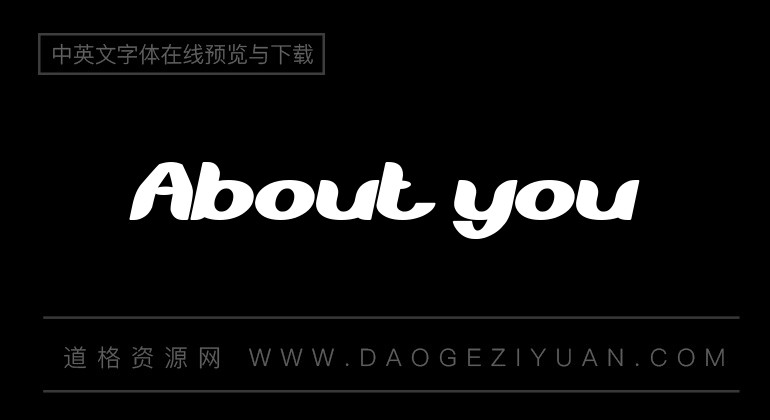
About you
About You 是一个比较流行的英文字体,它的特点是简洁明了,笔画舒缓,字形细腻,显示效果非常优美,适合用来制作各种设计作品,比如:海报、网页、广告、报纸等。它的字体结构清晰,字形自然,使用起来非常方便,可以帮助您在设计中更加精彩。
About you是一款非常不错的手写艺术字体,具有很好的视觉感,适合于文化类的宣传设计、商业类品牌的广告和产品包装设计以及个性化文字排版等较多场景。